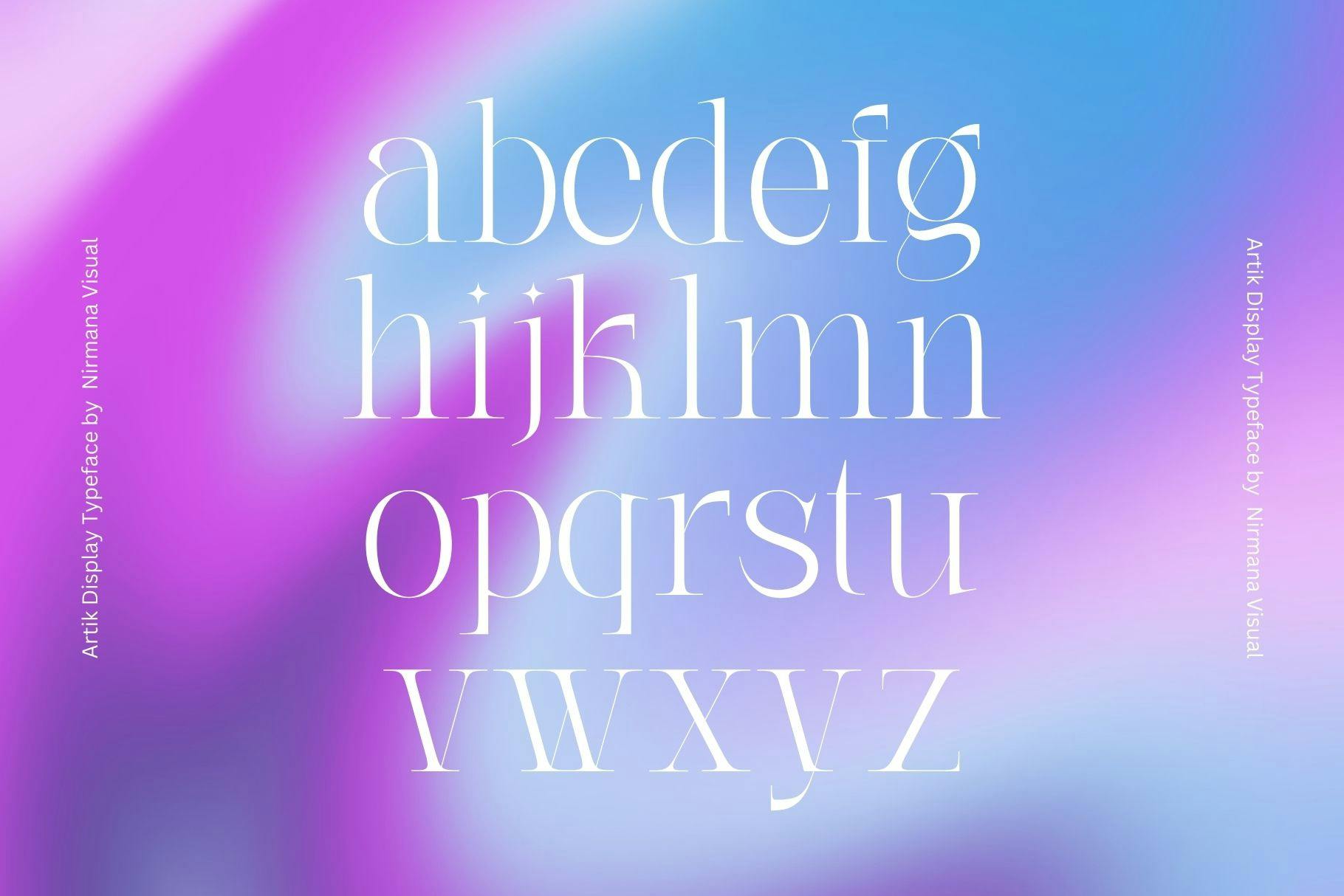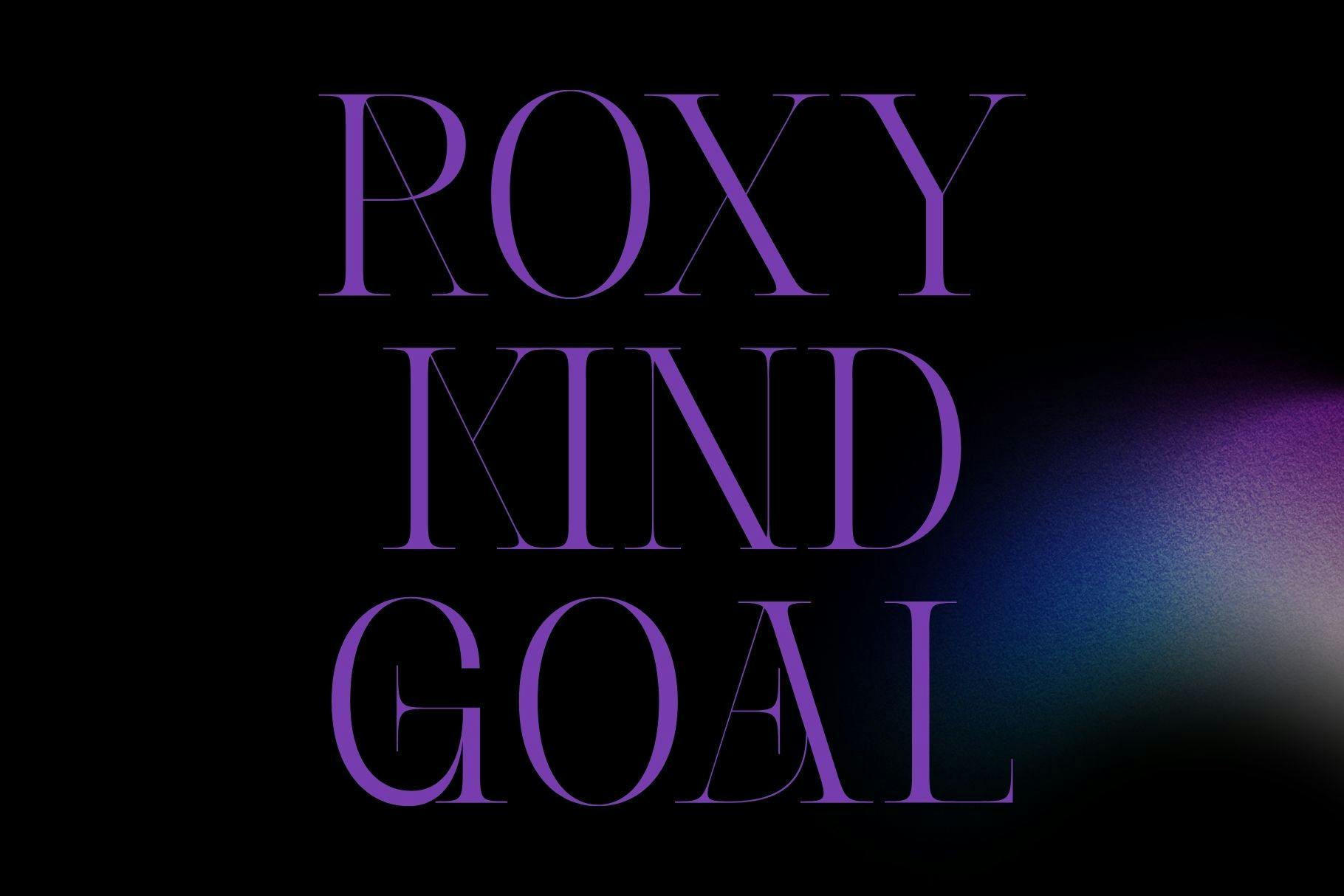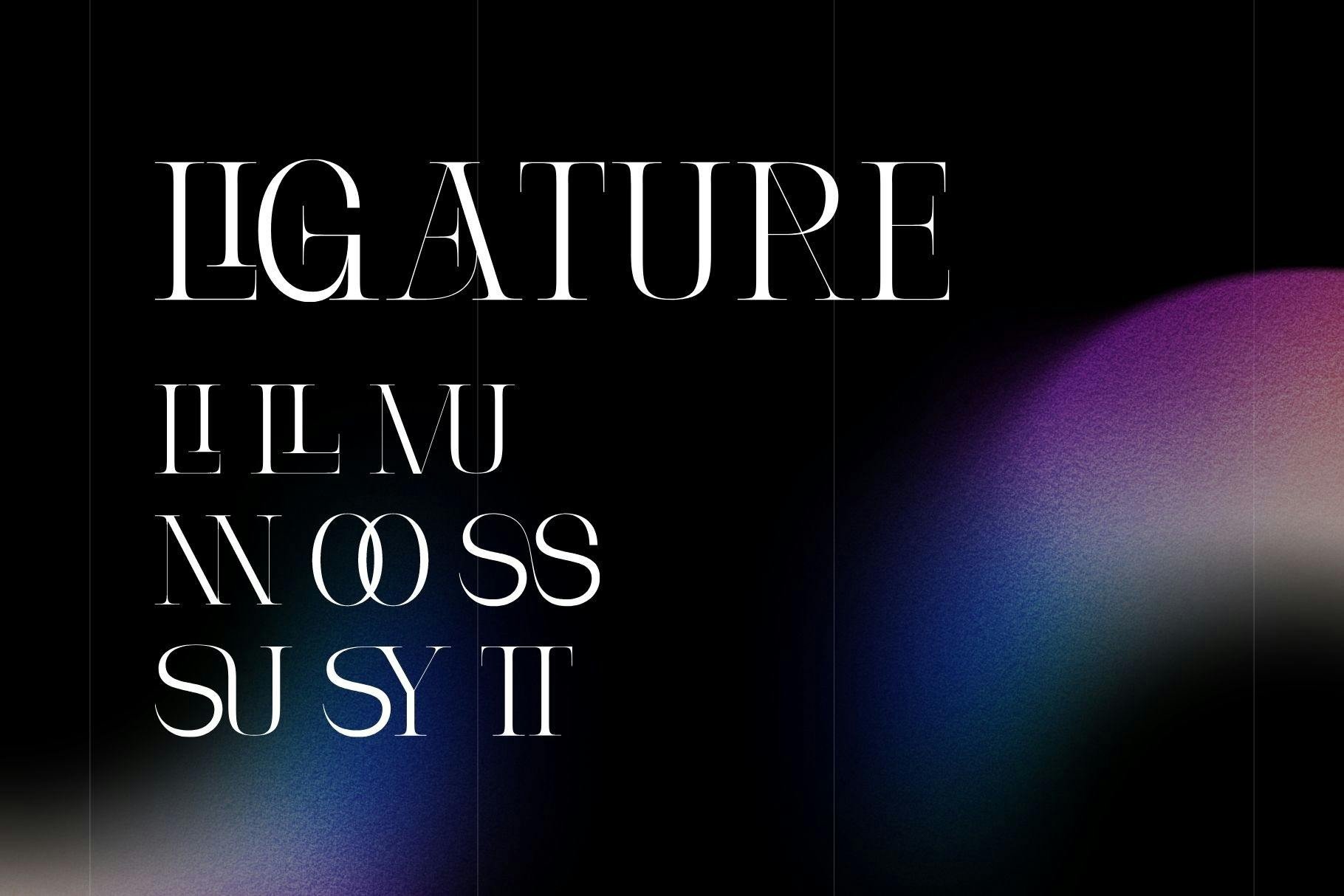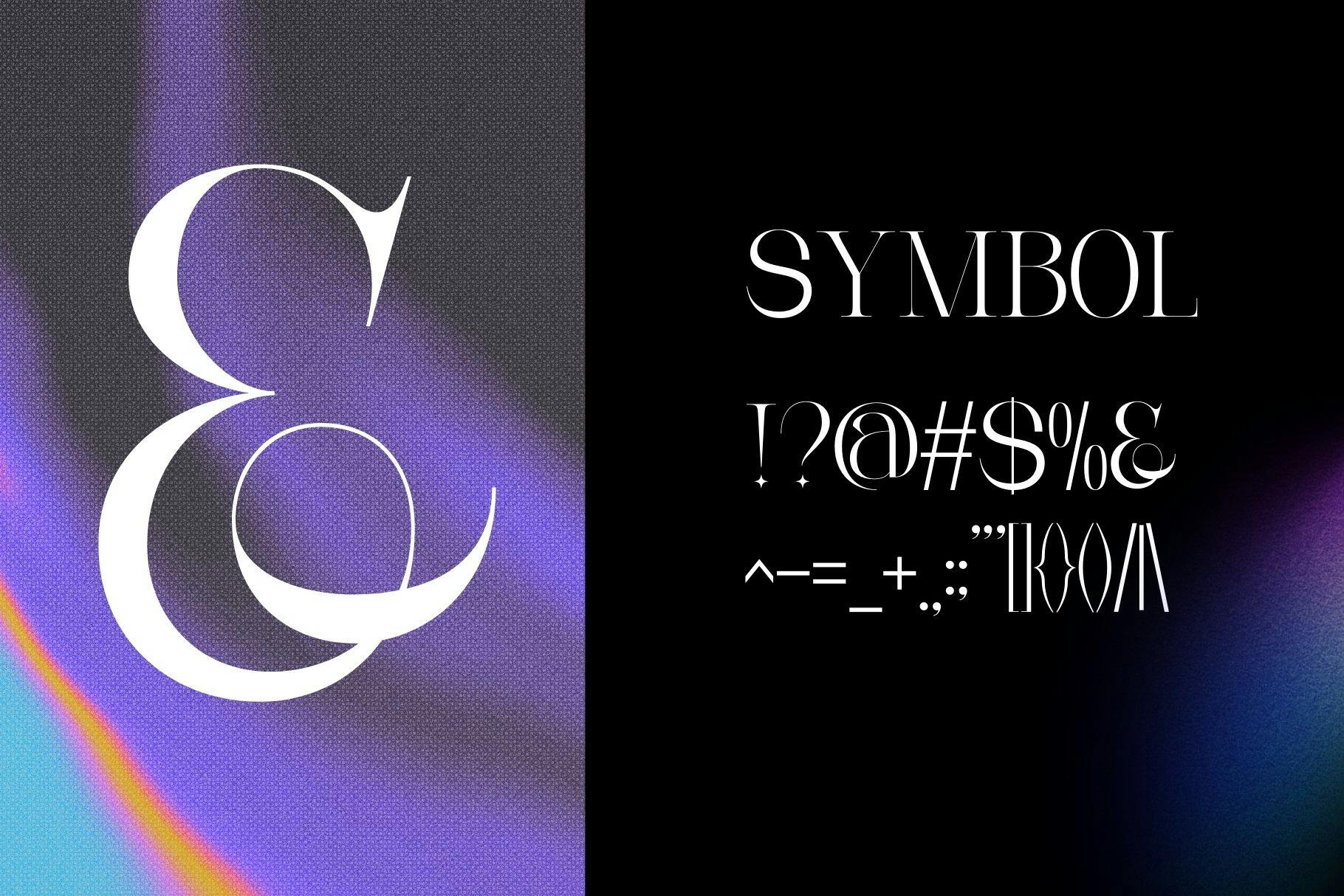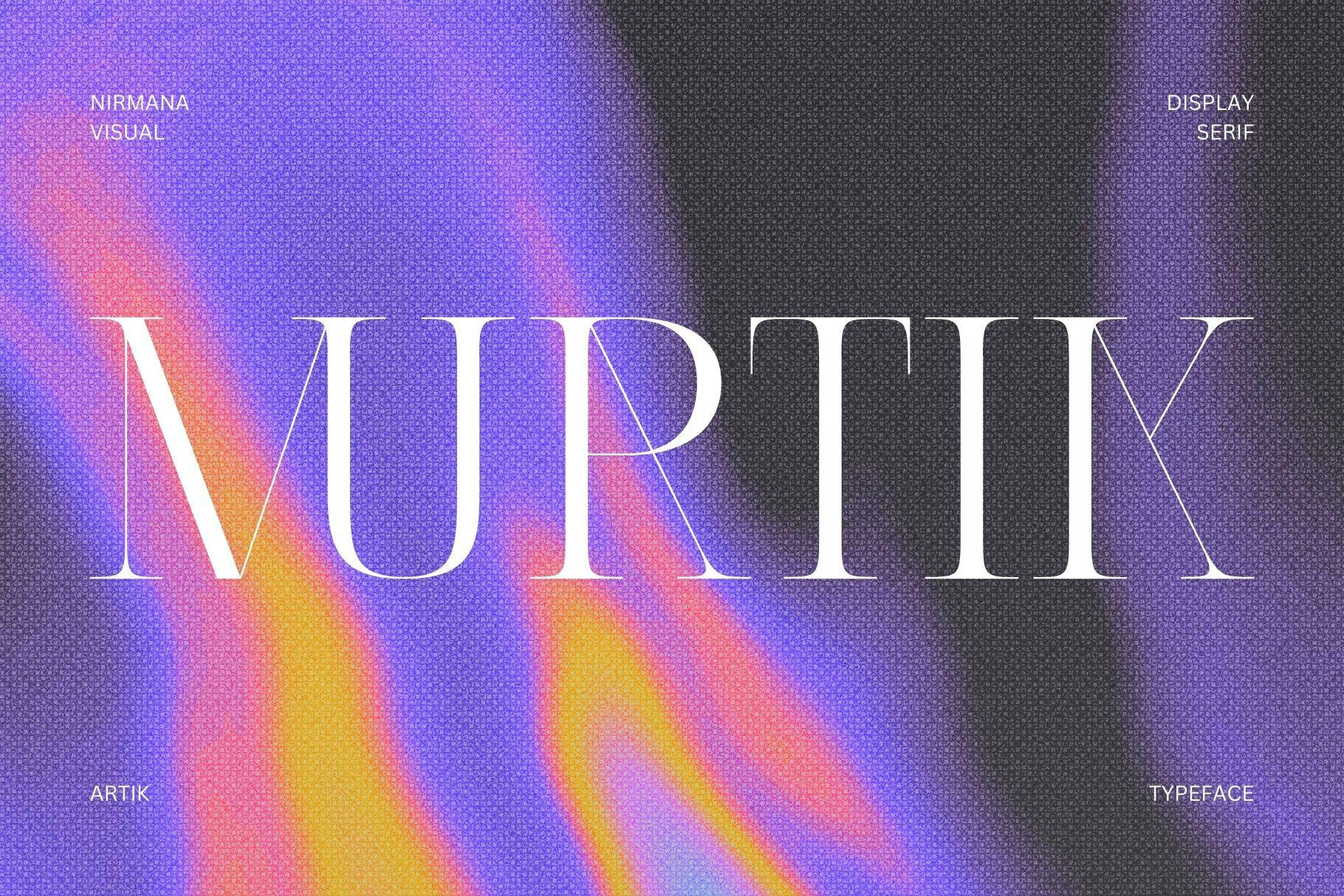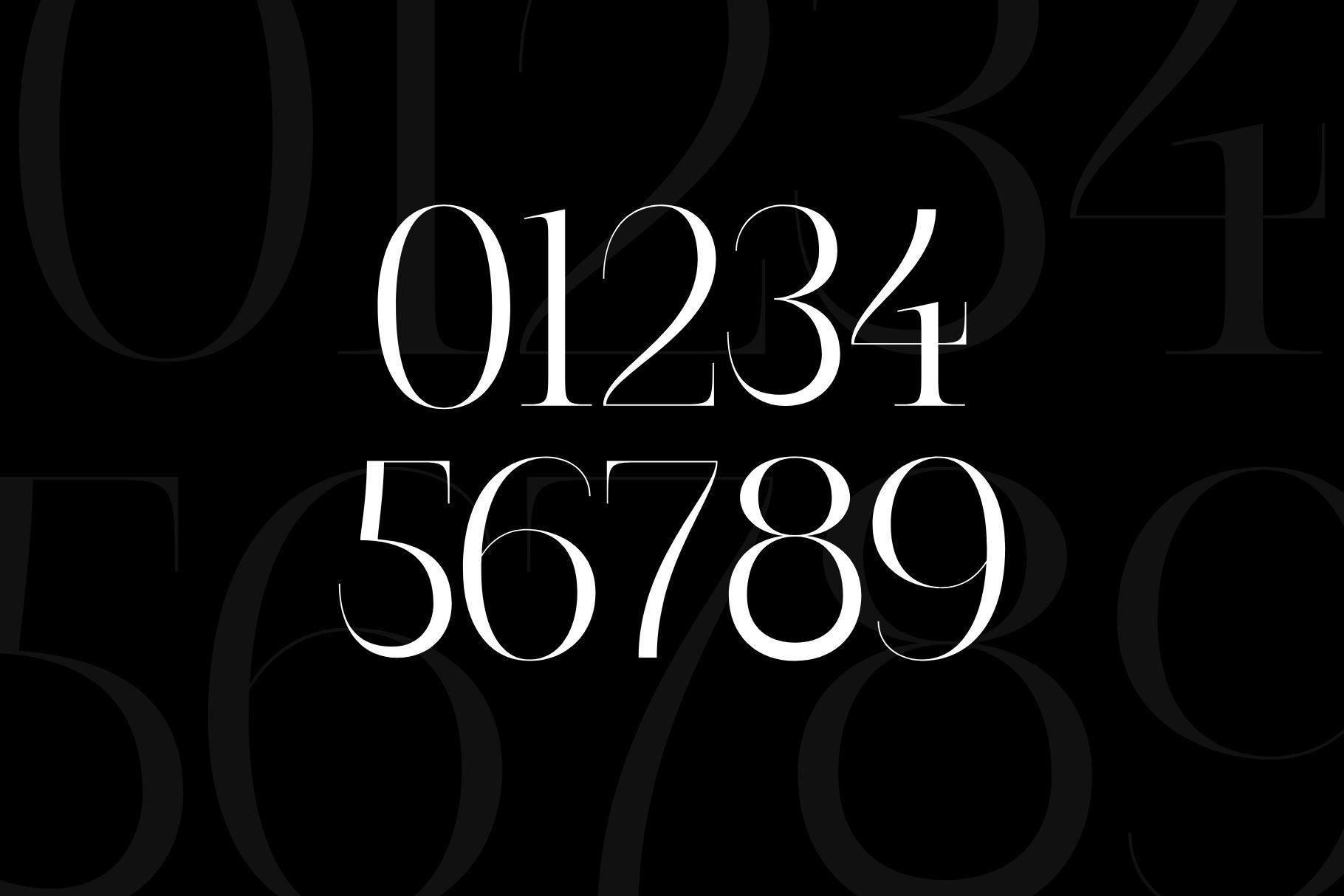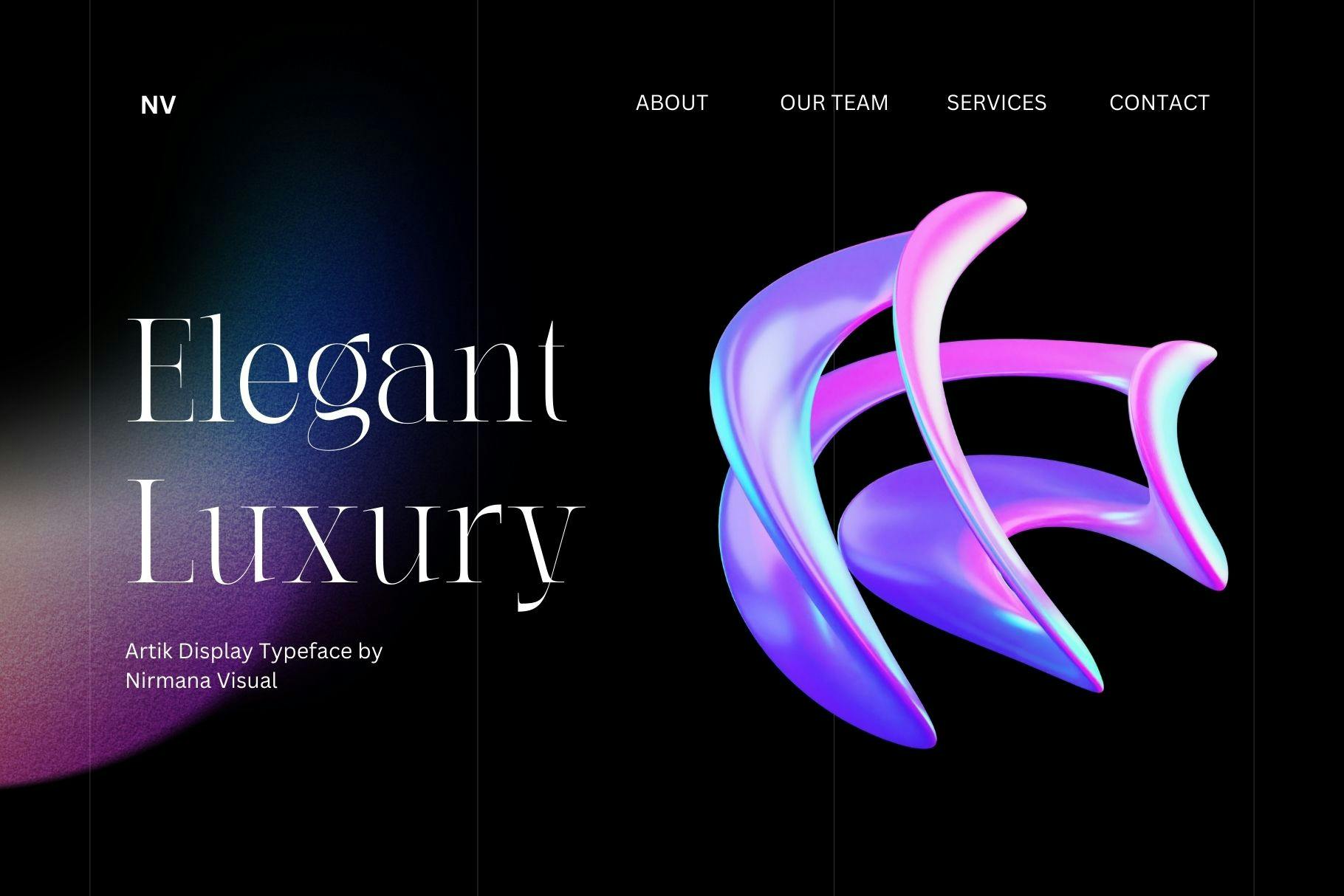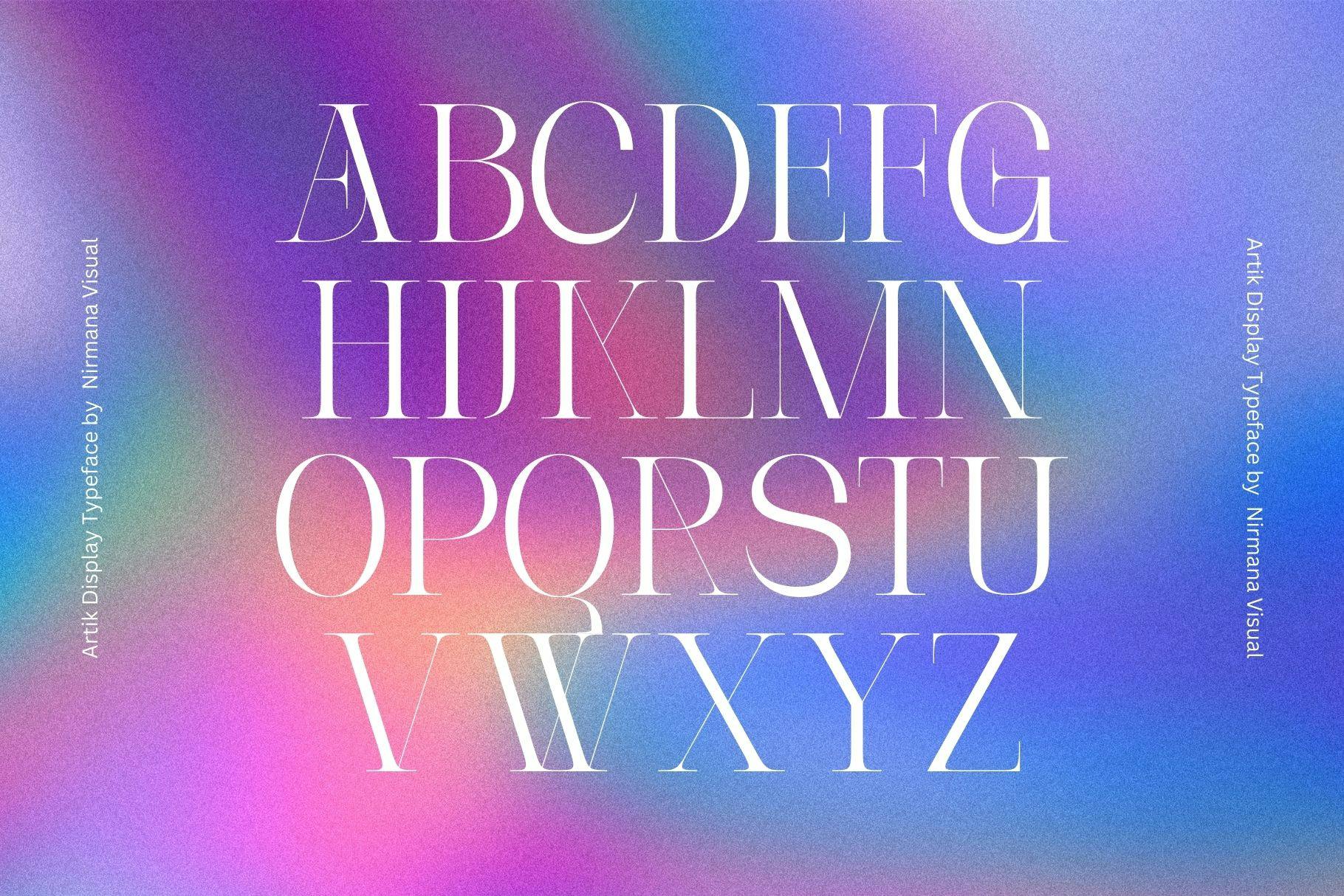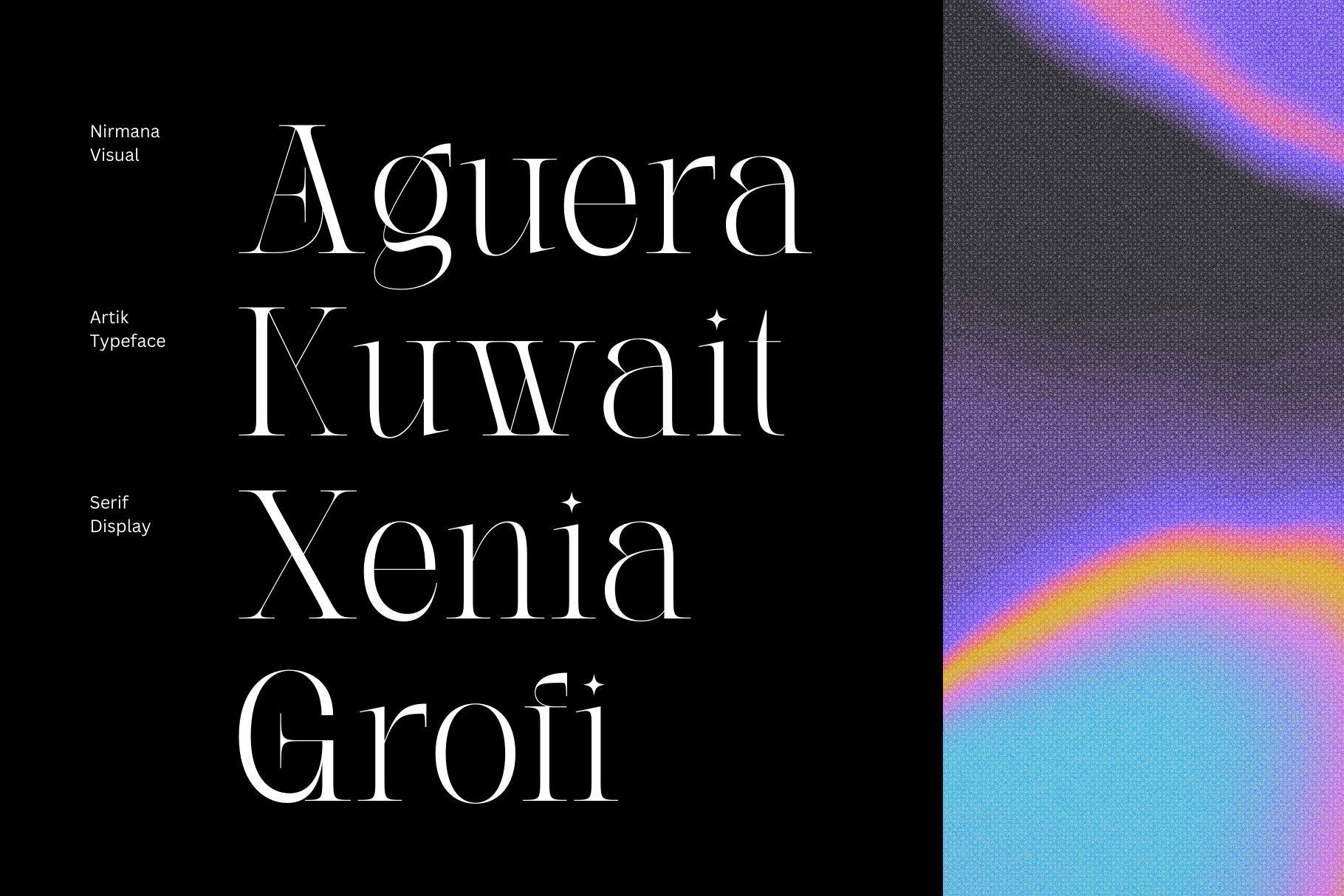
Artik - فونت مدرن، تایپفیس سرایف نمایشی.
فونت Artik هارمونی زیبای تایپوگرافی را برای تنوعی از پروژههای طراحی، از جمله لوگو و برندینگ، پستهای رسانههای اجتماعی، تبلیغات و طراحی محصولات ارائه میدهد.